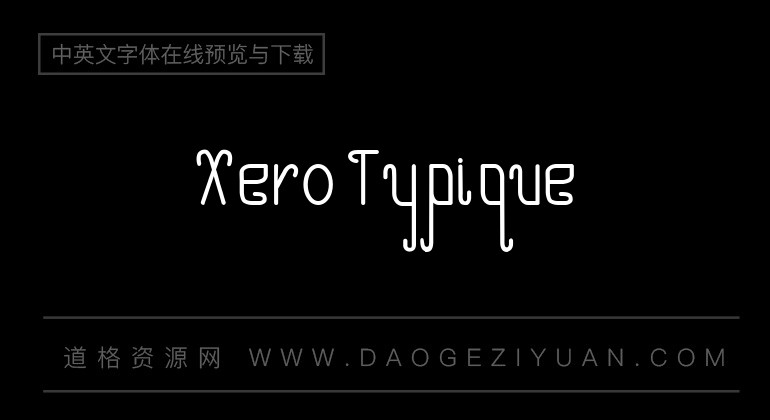
? Xero Typique 是一款灵活的多功能字体,由著名的西班牙设计师Xero Typique创作。它拥有独特的英文字母,可以用于各种不同的设计项目。它的字型特征简单明了,令人印象深刻,同时也有足够的空间来创造出一些有趣的设计。Xero Typique字体非常适合用于印刷品,网页设计,品牌标识,海报,标题,报纸和杂志等。内容介绍
Xero Typique是一款非常不错的手写艺术字体,具有很好的视觉感,适合于文化类的宣传设计、商业类品牌的广告和产品包装设计以及个性化文字排版等较多场景。